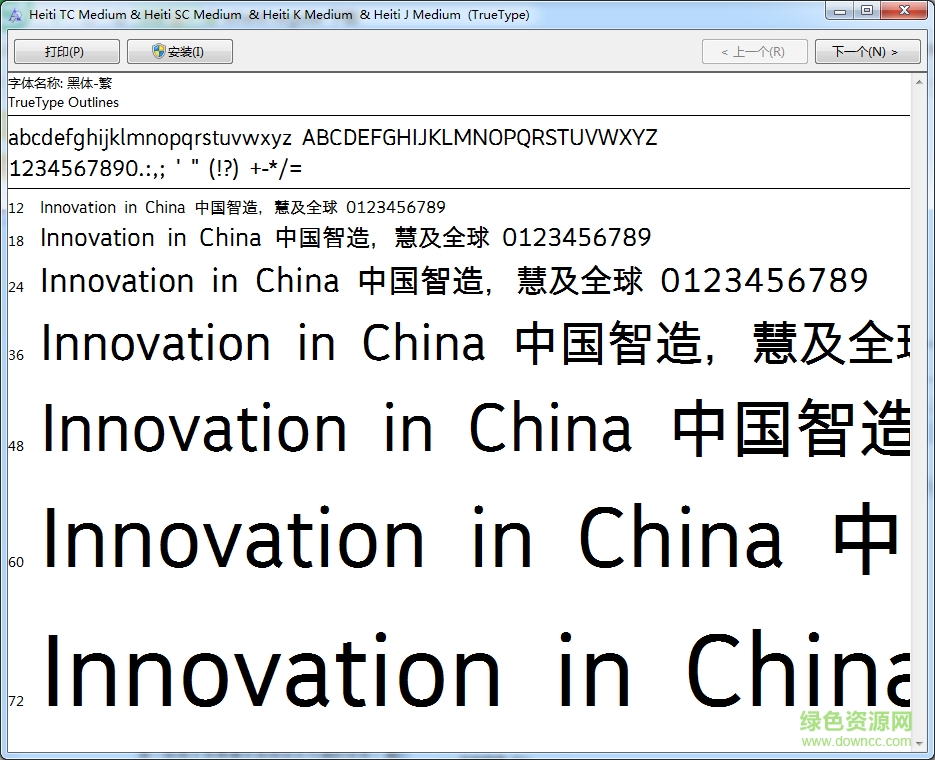
stheiti regular是一款比較常用的電腦字體軟件,字體端莊線條感十足,一鍵安裝便可輕松使用,使用廣泛深受廣大用戶喜愛??靵砭G色資源網(wǎng)下載體驗(yàn)吧!
stheiti regular是一款應(yīng)用范圍非常廣泛的字體,此款字體線條圓潤(rùn),干凈整潔,字型端莊大方、表現(xiàn)力強(qiáng),可直接導(dǎo)入至ps中使用,安裝方法簡(jiǎn)單,喜歡的朋友歡迎來綠色資源網(wǎng)下載!